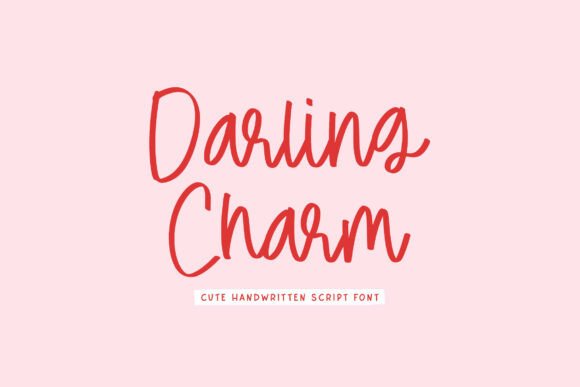
Darling Charm
Пошук відповідних елементів дизайну може бути складним, але Darling Charm пропонує виняткову колекцію, яка миттєво покращить вашу роботу.
Незалежно від того, чи створюєте ви продукти POD (друк на вимогу), весільні запрошення або графіку для соціальних мереж, Darling Charm стане ідеальним вибором.